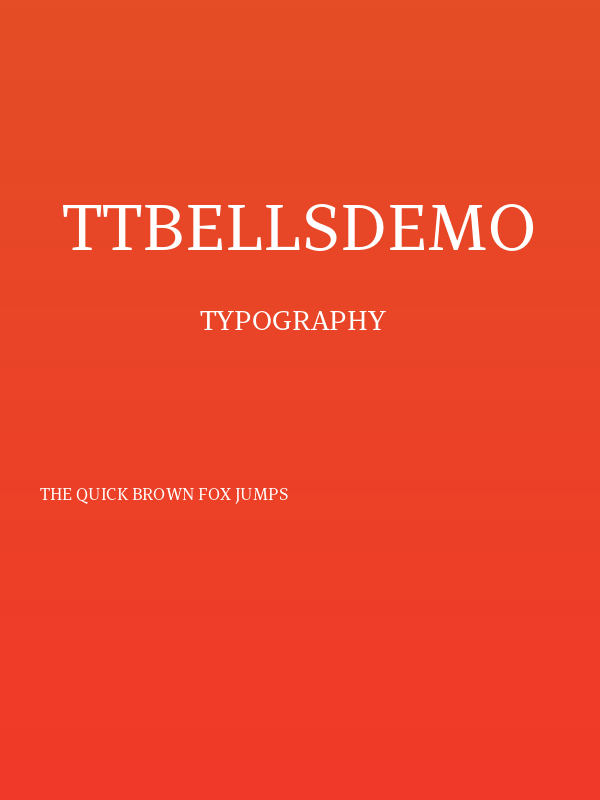
TTBellsDEMO Font
✎ Serif
| الفئات | Serif |
| النمط العام | Classic |
| حالة الاستخدام | Headlines, Body text, Logos |
| مشاريع مقترحة | Ideal for editorial design, book covers, formal invitations, and branding projects that require a touch of sophistication. |